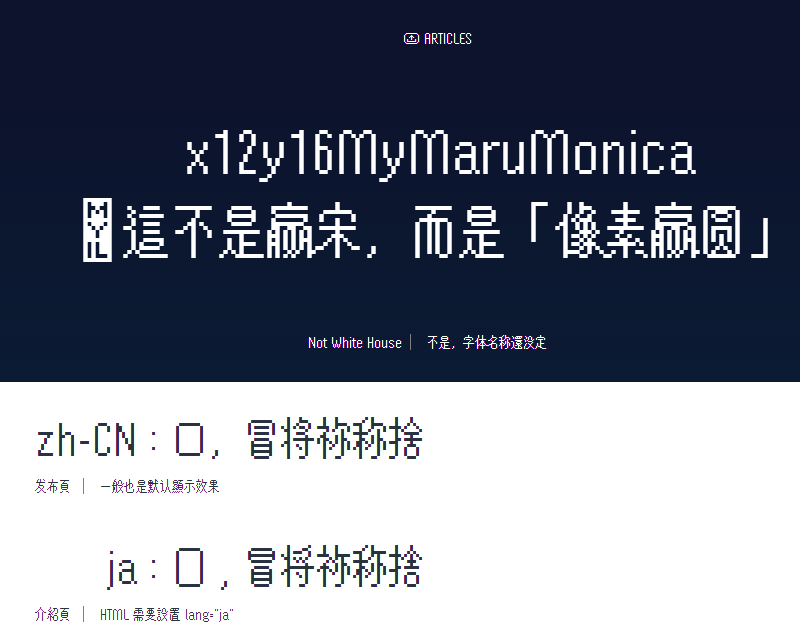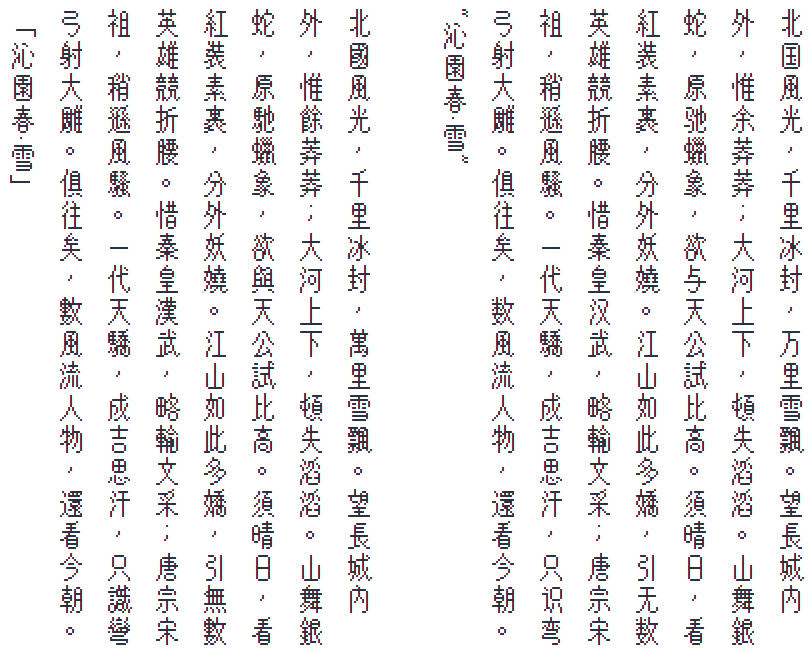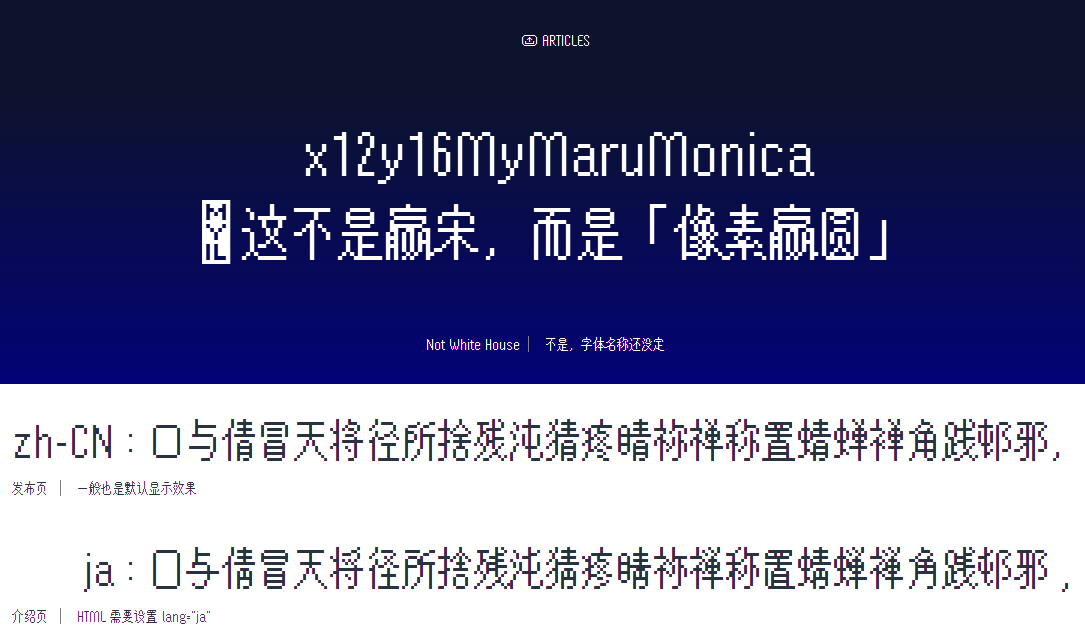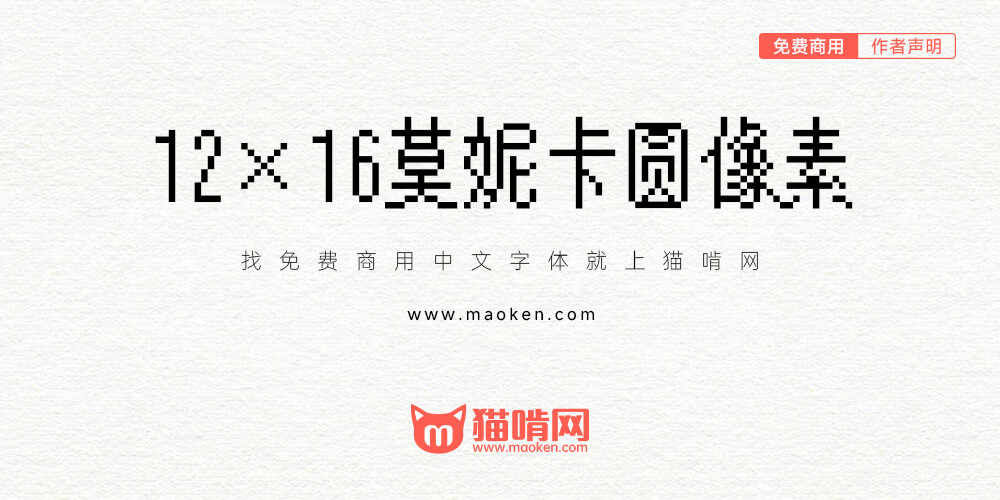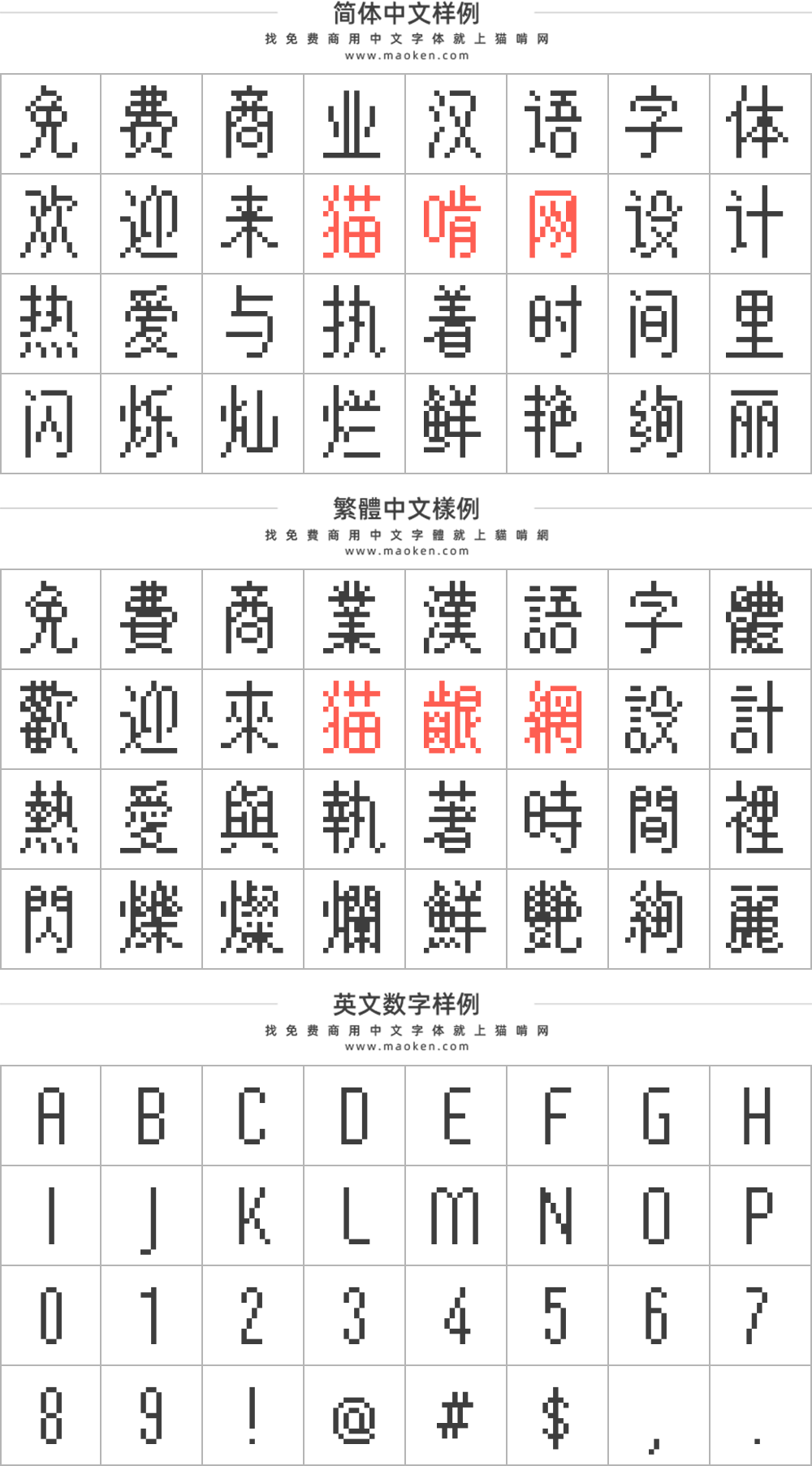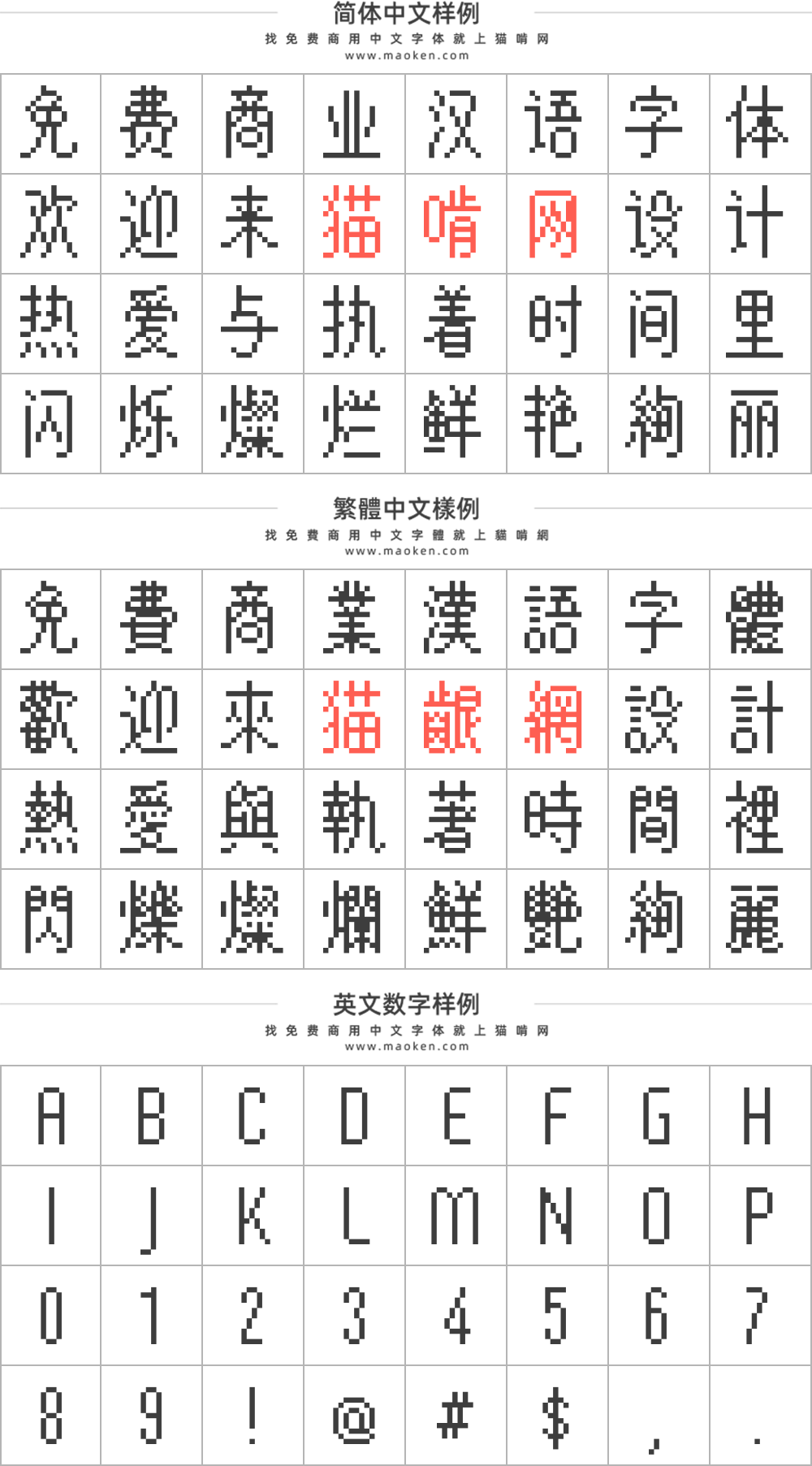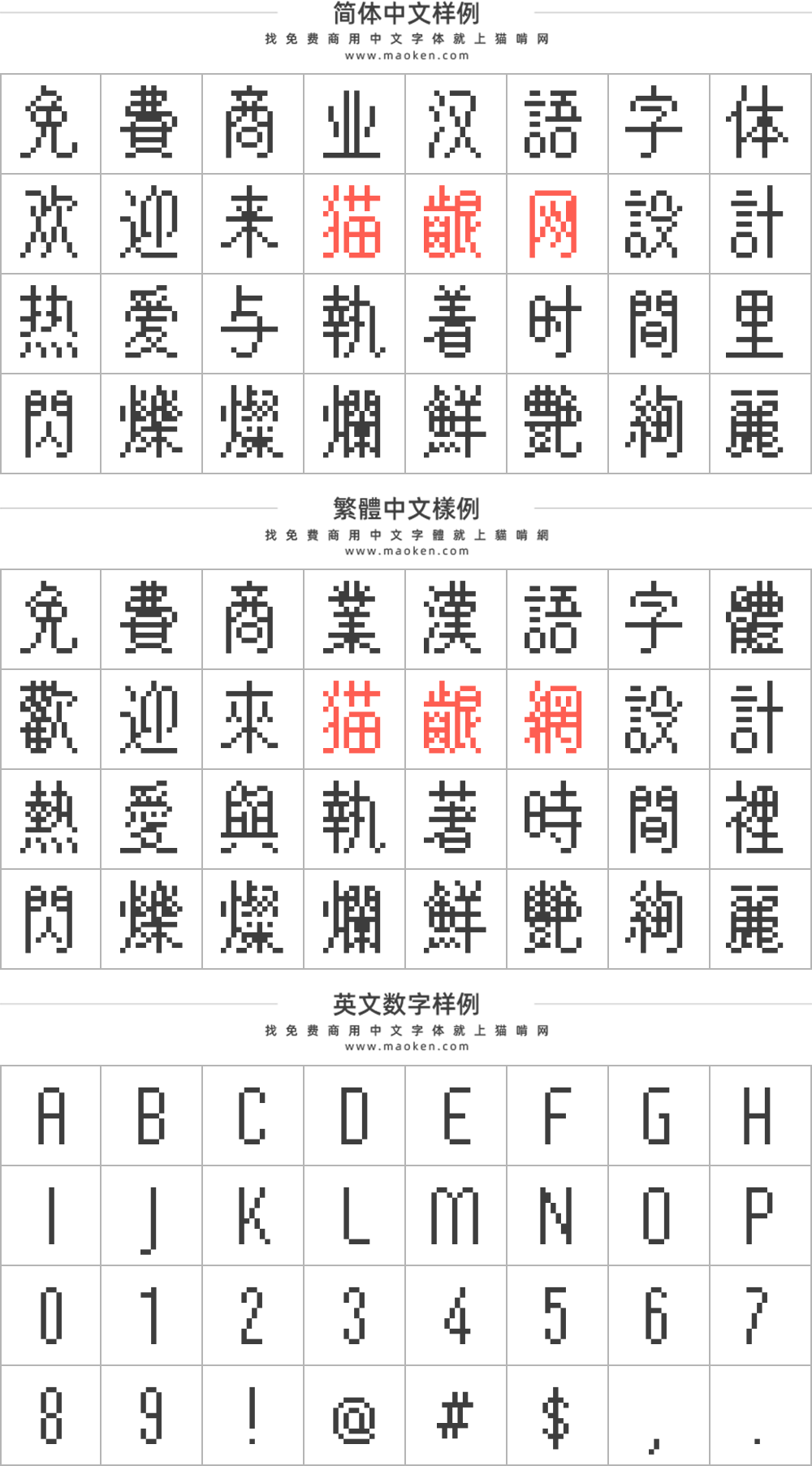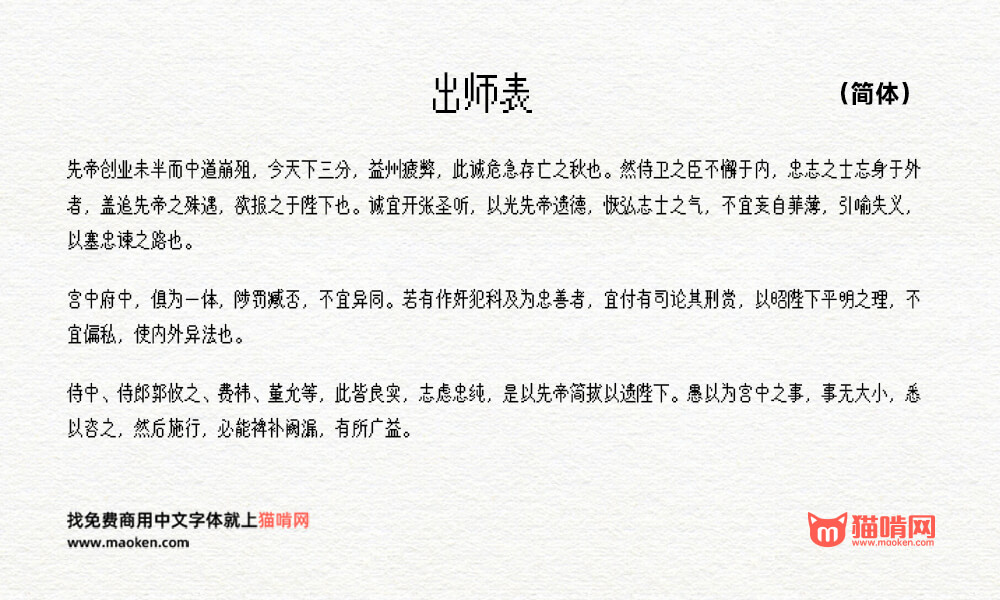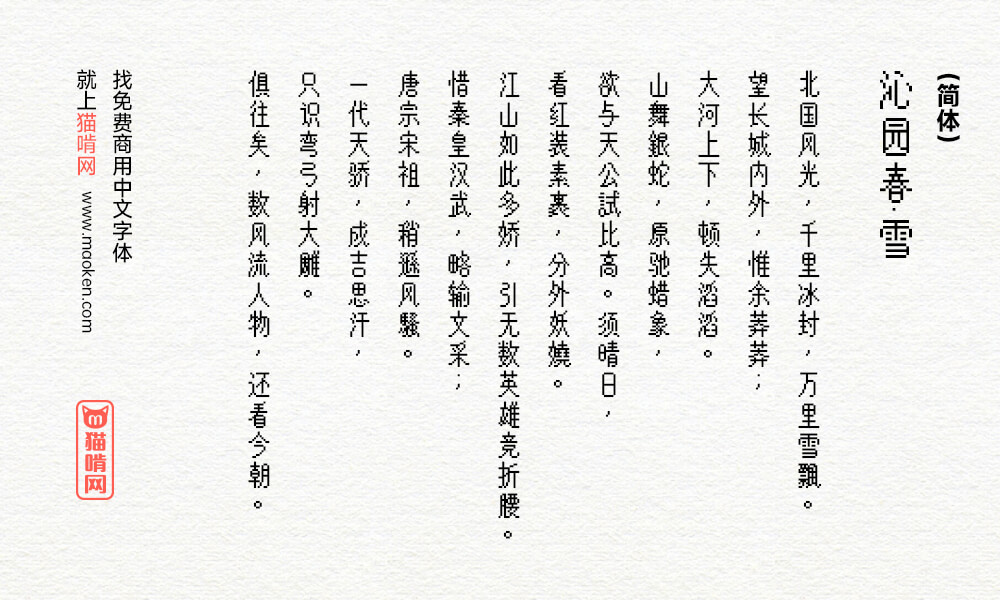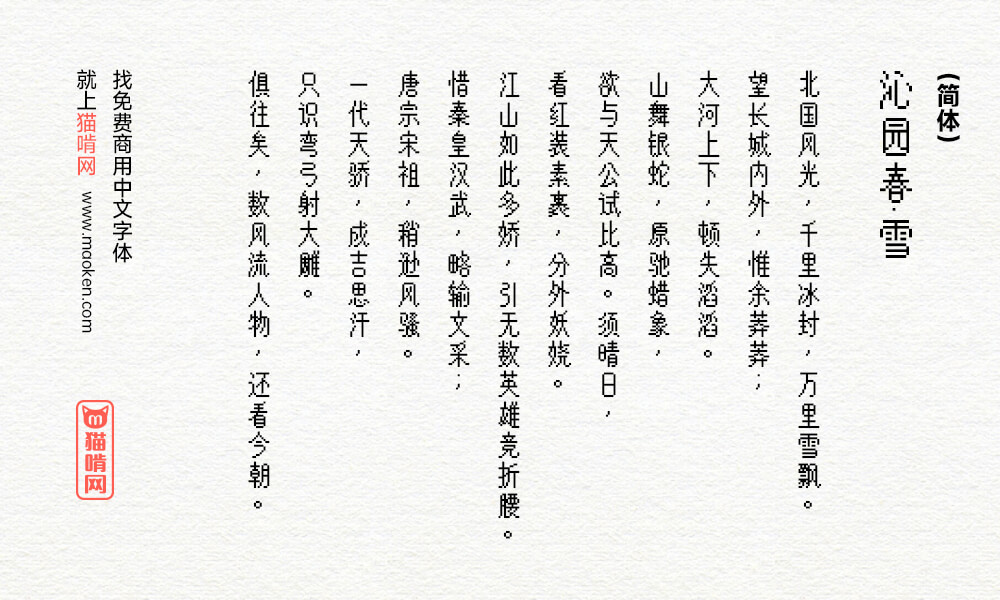
12×16莫妮卡圆像素:莫尼卡像素圆体补简计划
某日本像素游戏(MORSOMNIA:0)用到了像素字体“x12y16pxMaruMonica”(猫啃有收:莫妮卡像素圆体),其特点为12×16的窄圆体,汉化组甚至找不到类似的中文像素字体。
注:虽说是“像素”字体,但原作不含点阵,字形实际是矢量勾勒像素块,使用时需将字号设为16px的整数倍以取得锐利像素效果。
看了汉化文本缺字统计,我觉得只缺六百多字的话,今年内应该是可以补完的,于是先做了个临时预览版(截至 Ver2025-5-30 只做了3百字,其它几百暂用类似日标字顶替,如“绘”,繁体为“繪”,我用“絵”),提前放出是吸引感兴趣的人参与补字。2025年6月18日补完游戏所需全部6百字,见下方字数统计
与原作的差异
“绘、絵”尚且码位不同,而日文的“冒(冒,U+2F8D2)、将、称、捨”等字与中文码位完全一致,字符上不能区分,于是我在保留原作字形、字序的前提下,在尾部追加了中式字形设为默认,给原字体字形添加了loclOT特性以备日区环境调用,例如浏览器遇到lang="ja"即可切换为原日式字形。
我感觉原作逗号做错了,但仍保留,并另作一个“中式逗号”
汉化组提供使用本字体效果(旧版)
还额外添加了liga calt特性用于中文标点,例如在前述游戏里文字有勾边,原字体的破折号,眼尖的玩家能看见中间有断开,本改版则绝不会断:因为用liga将“——”替换为1个字符“⸺”
虽然我希望对原作无损修改,但其实改动了一字:口。原作里口囗完全一致无法区分,考虑到“口”占太满就上下缩小1像素,将“囗”设为口的日区字形。
“傻瓜偏旁”
也许有人要问,相比其它人的,此版补字有什么优势?我为此字研了一个技术:傻瓜偏旁。
新款造字软件如Fontra,对造中文有个奇妙的支援,是可变字体引申出的功能“智能偏旁”,比如在预先做好某偏旁最宽最窄两极端之后,就可以无级调节宽度、在所有包含此偏旁的汉字里复用它。
但像素字体不存在无级调宽——比如一般不许0.25个像素——我只能很傻瓜地预制了偏旁的每个需要的宽度字形以备复用。因ttf复用字形不太占文件体积,这导致我的字体比原作.ttf体积还小。
(旧版,2025-9-7版见此)
参与补字者可以直接用预制偏旁肆意拼字,想想就爽🤪
伲呢坭妮抳昵柅狔秜胒蚭跜铌
显然尼旁分为两部分更方便
另外,还补充了多重映射:⤹⤸ⒶⒷⓍⓎ⮹⨂⊚🟗🟕⌨⊝⨁➖➕⌂,这些是原作就有字形但放私用区的。而原作中特地放私用区的游戏符号皆在本作中保持一致。
晩(晚)像素里不必区分也合并映射了,但若你的游戏里有意要区分这2字的话也请告诉我。
也没经过几个月,元素周期表已于2025-7-15版补全了……仍期待大家参与(旧版字体)
2025年8月3日起,包含全部藏文,并针对一些词汇单独编写了特性。但注意藏文需要高级排版,由于原日文字体天然的度量限制,恐怕难以按正确规则排版藏文。下图右下角展示了 不支持→支持 排版特性的情况。
(2025-8-3旧版)